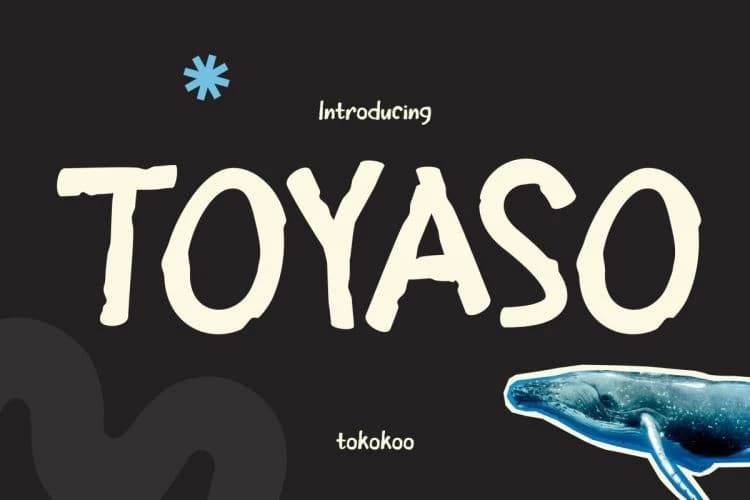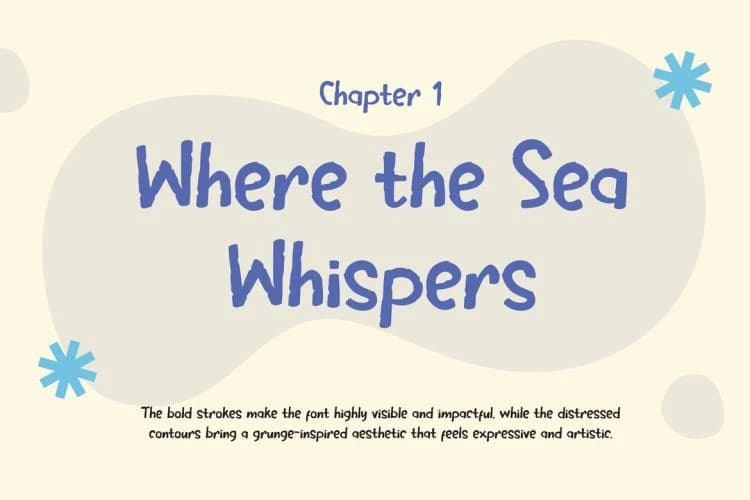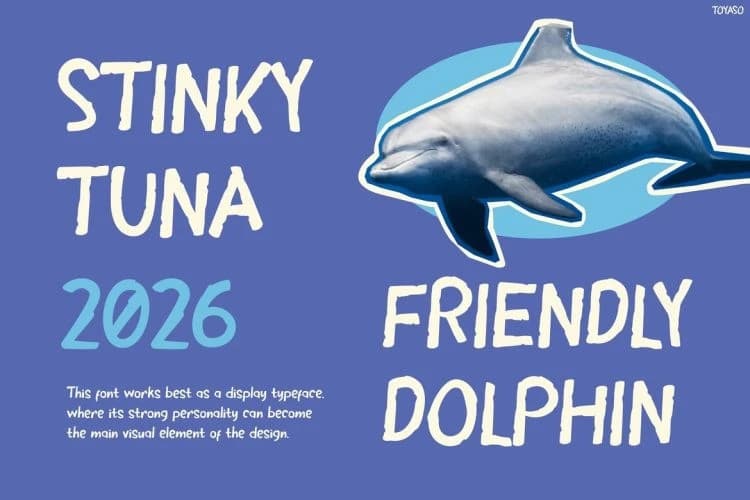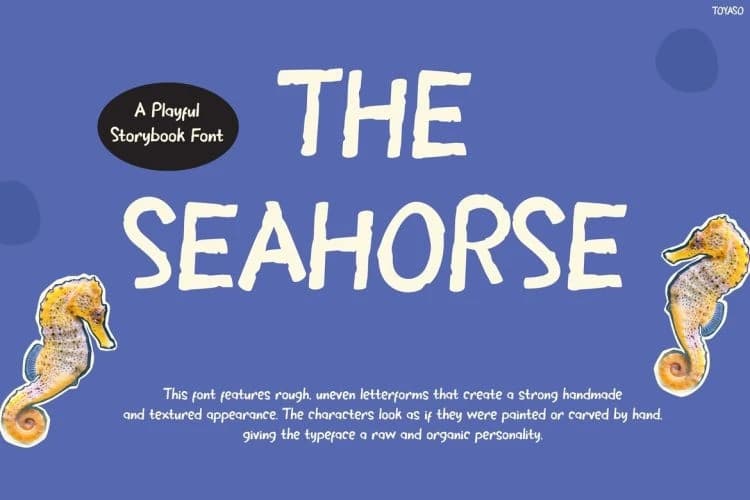
Toyaso Playful Font
Toyaso Playful Font, okyanus maceralarından ve çocukların hikâye anlatımından ilham alan oyuncu ve organik bir gösterim yazı tipidir. Yumuşak, elle çizilmiş şekilleri ve hafif dokulu çizgileri doğal ve samimi bir görünüm yaratır.
Toyaso Playful Font, okyanus maceralarından ve çocukların hikâye anlatımından ilham alan oyunbaz ve organik bir gösterim tipi yazı tipidir. Yumuşak, el ile çizilmiş şekiller ve hafif dokulu çizgiler doğal ve samimi bir görünüm yaratır.